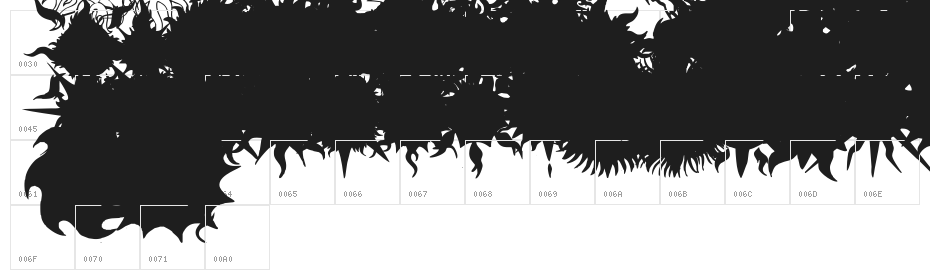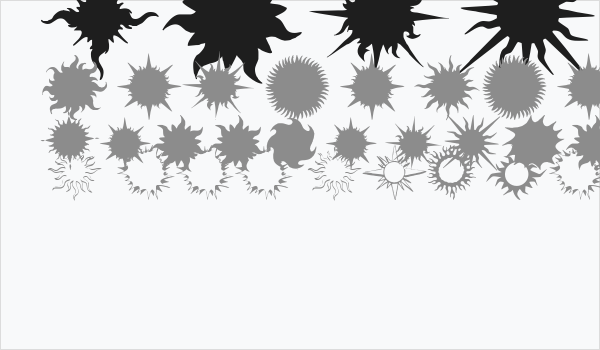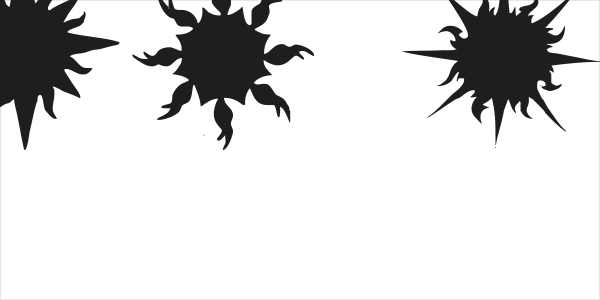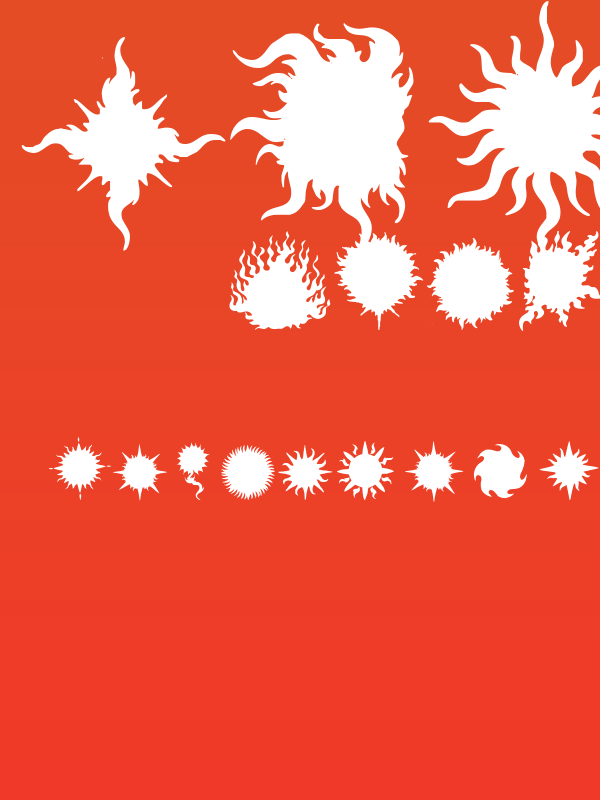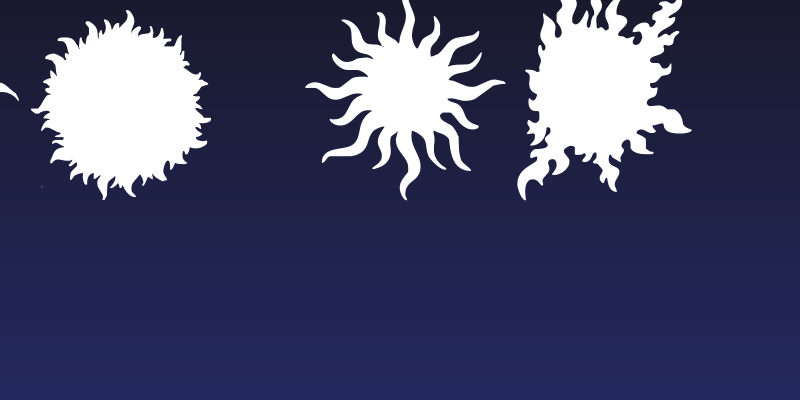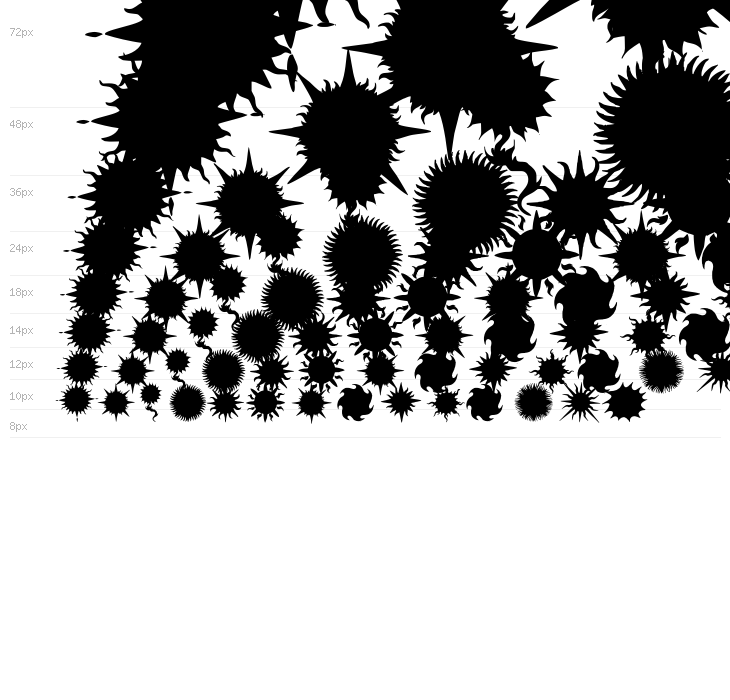
Flaming Stars Splatters Font
| Stile generale | Decorative, Dynamic, Abstract |
| Caso d'uso | Graphic elements, Icons, Visual effects, Not suitable for body text or headlines. |
| Progetti proposti | Posters, album covers, comic book effects, digital stickers, graphic design accents, party invitations. |